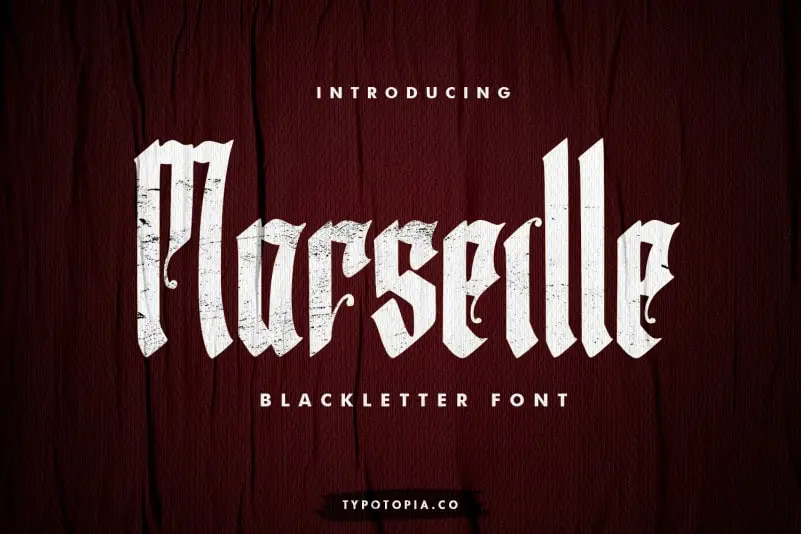
A Marseille Blackletter Font é uma escolha única para quem busca uma tipografia com um ar de elegância e modernidade ao mesmo tempo. Introduzida recentemente, esta fonte inclui letras maiúsculas, minúsculas e pontuação, além dos caracteres internacionais, oferecendo flexibilidade incomparável em seu design. Marseille se destaca especialmente para aplicações que exigem um estilo elegante ou artístico. Seja para logotipos criativos, embalagens modernas, invitations de eventos especiais ou até mesmo para criar mensagens de marketing atraentes e memoráveis, Marseille tem o poder de adaptar-se aos mais variados formatos. Sem dúvidas, é uma excelente opção para quem busca um toque distintivo em suas criações.